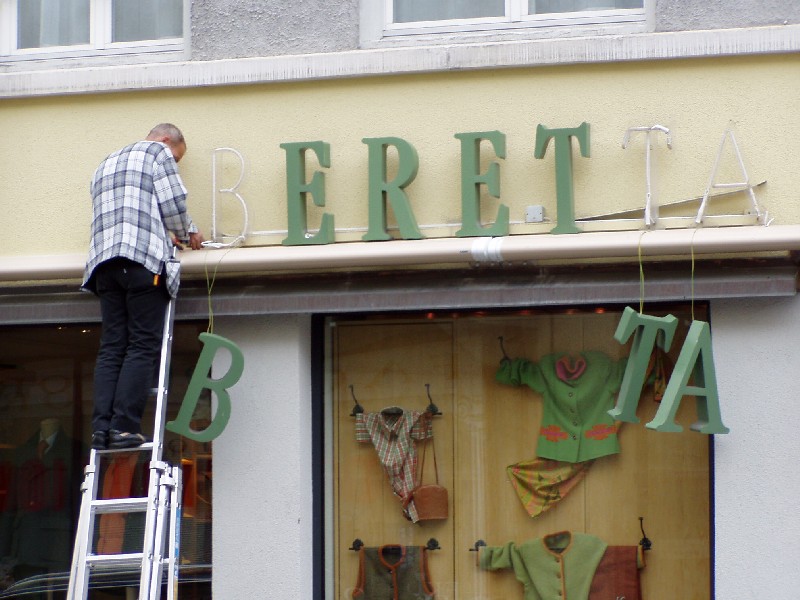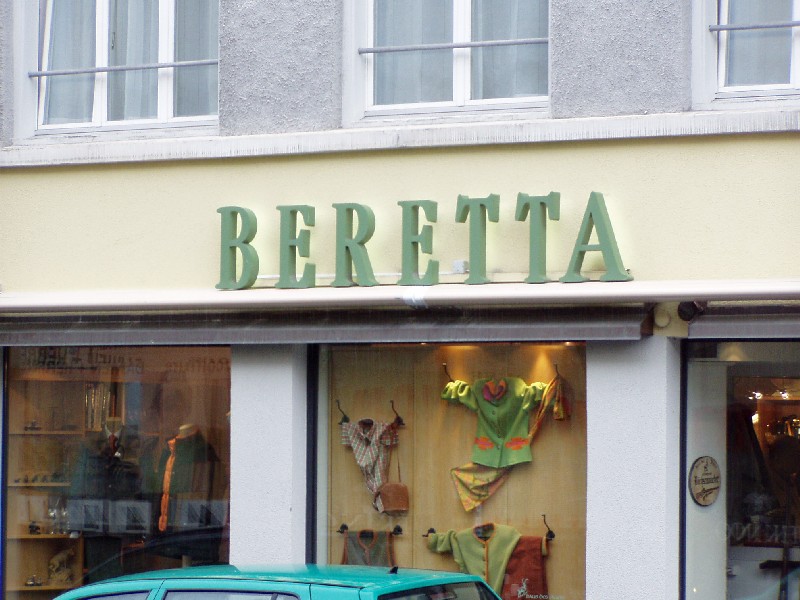
モジにかかわるある風景
スイスのサンモリッツという町で見かけたある風景…。
最初に通りかかったときは、おじさん大きなアルファベットと格闘中…。なるほど、こんな構造、こんなからくりだったのか…。ブラブラと風に揺れているB,T,Aがかわいらしい。おじさんのお取込中にハイ、パチリ
!このまま見ていたかったけど、ちょっと観光に出かけました。
町の散策もだいたい終わり帰り道…。おじさんの姿は既になく、きれいなスペースでアルファベットが並んでいました。お店もオープンしていました。メデタシ、メデタシ!
町にはいろんな書体のアルファベットが自然な姿でいろんな場所におさまっていました…。やはり地元のモジなんだなぁ…と実感!その町の建物や雰囲気と合っていて…なんかいい感じでした。